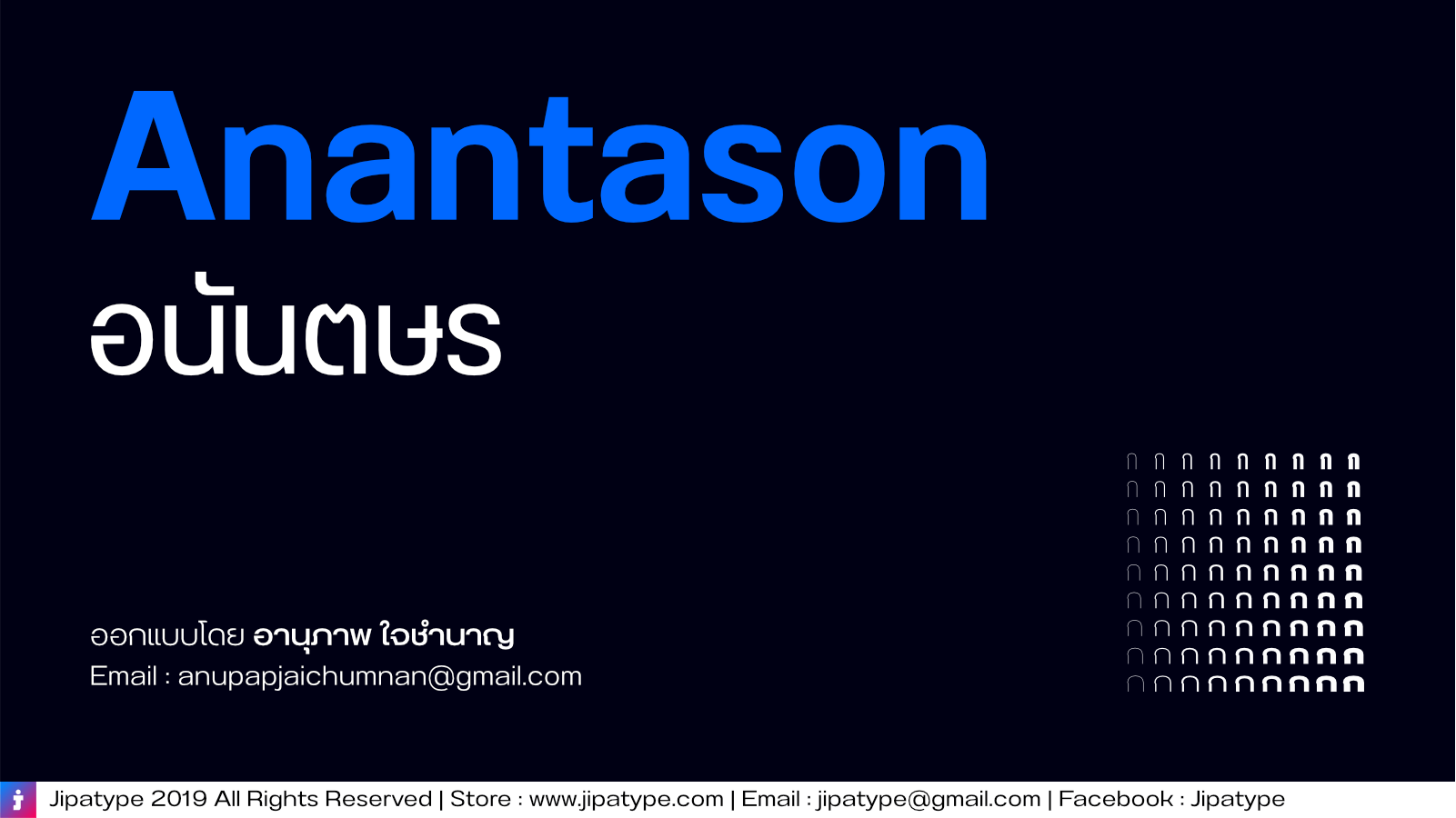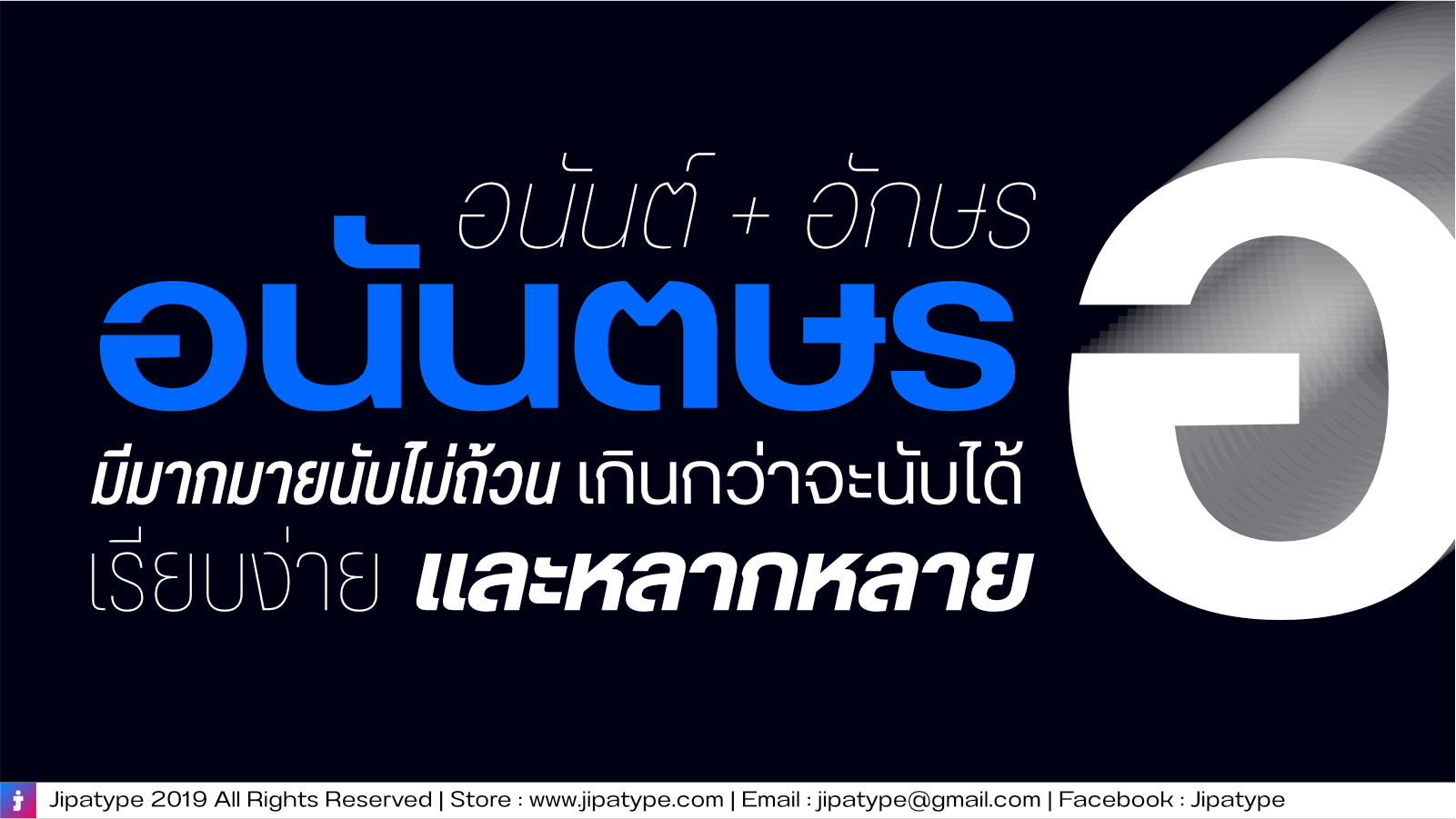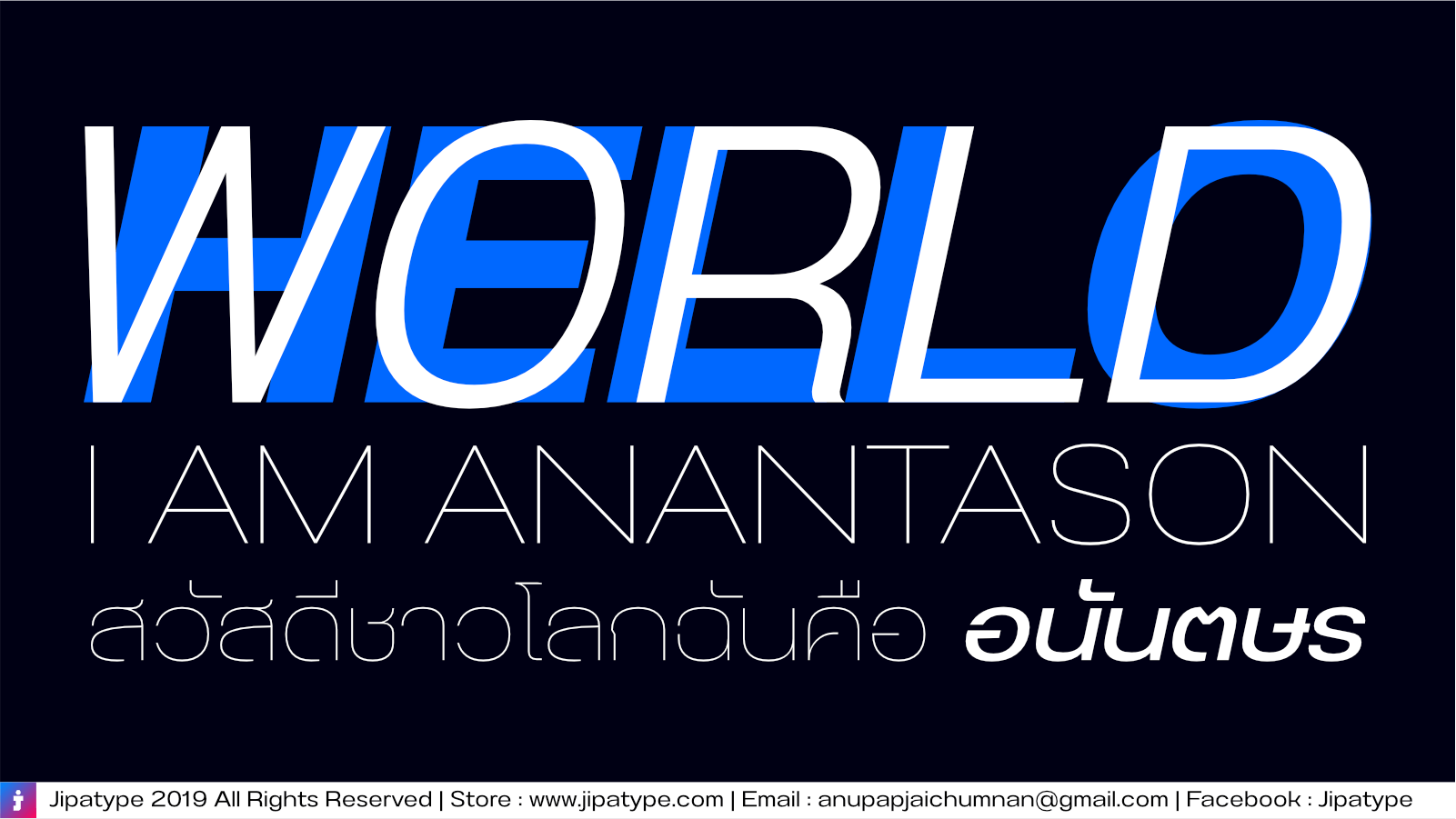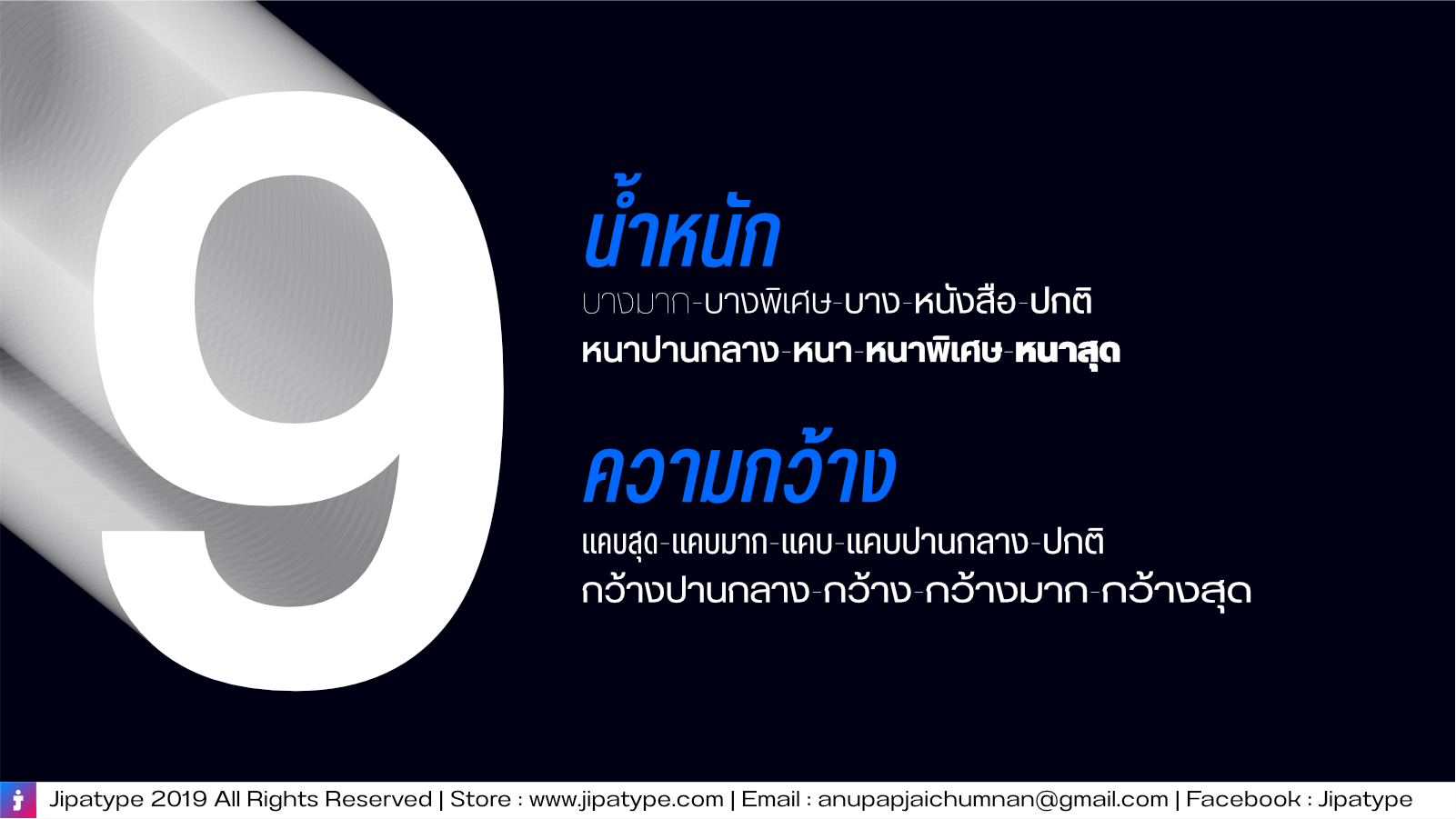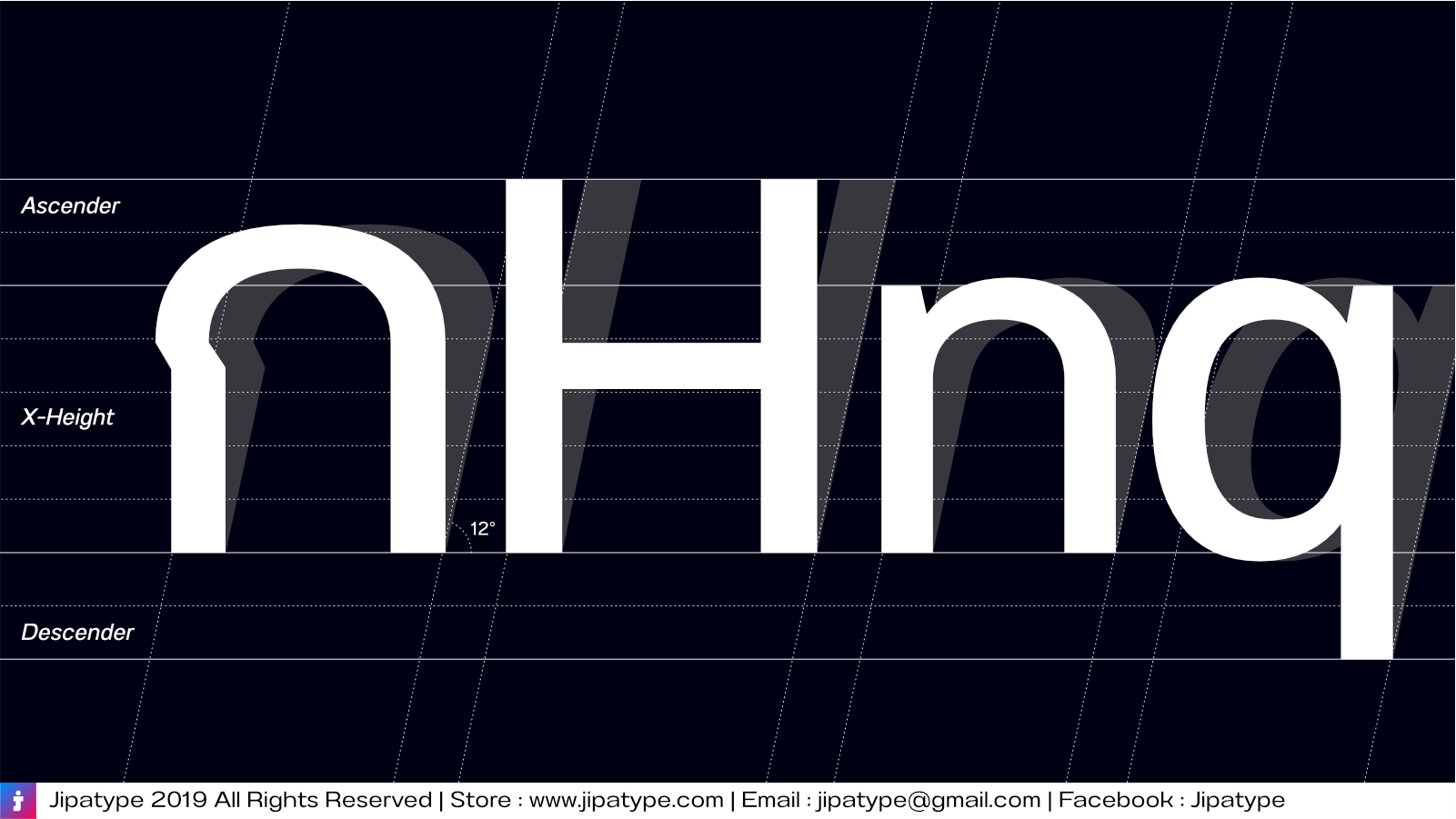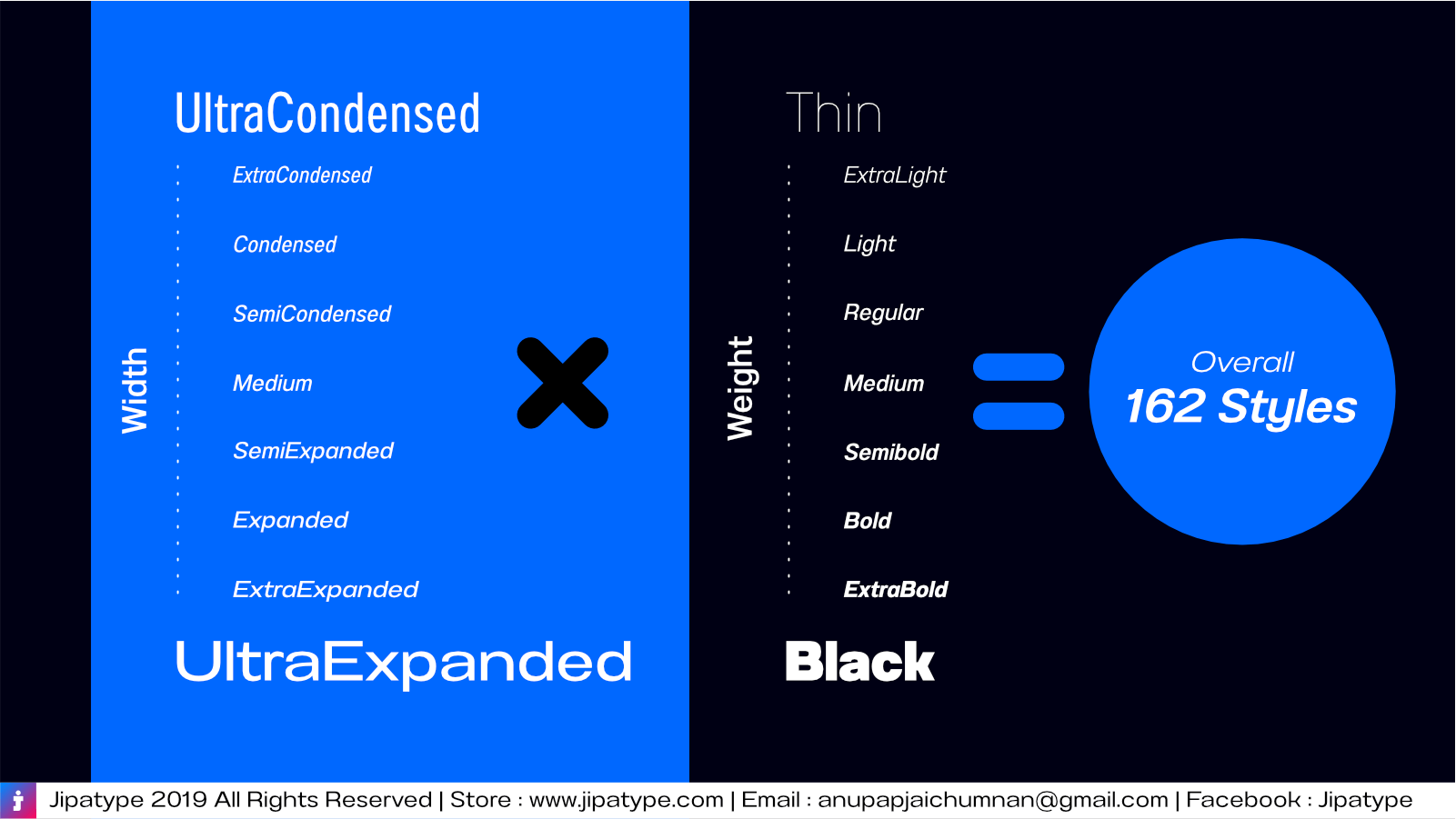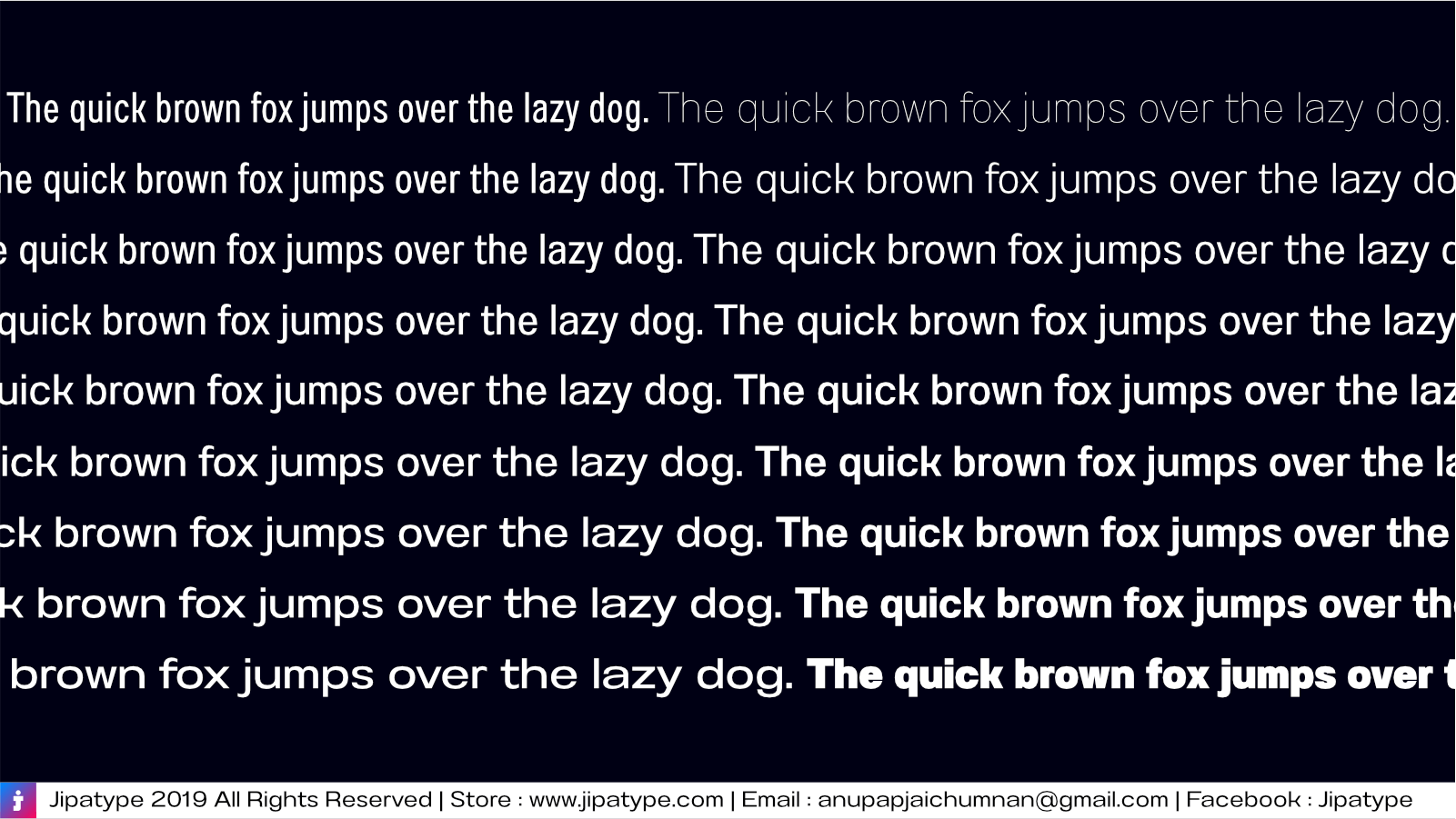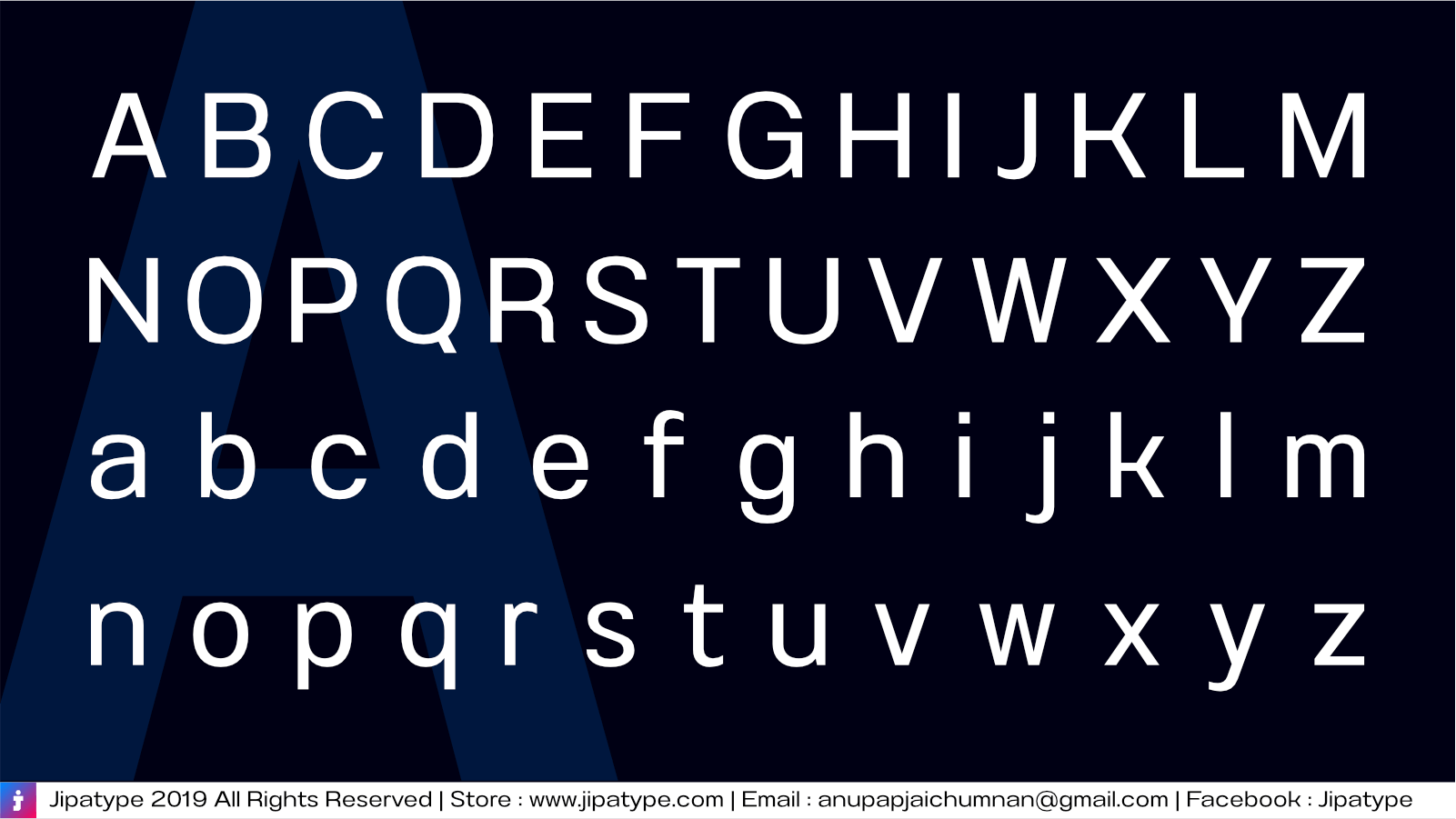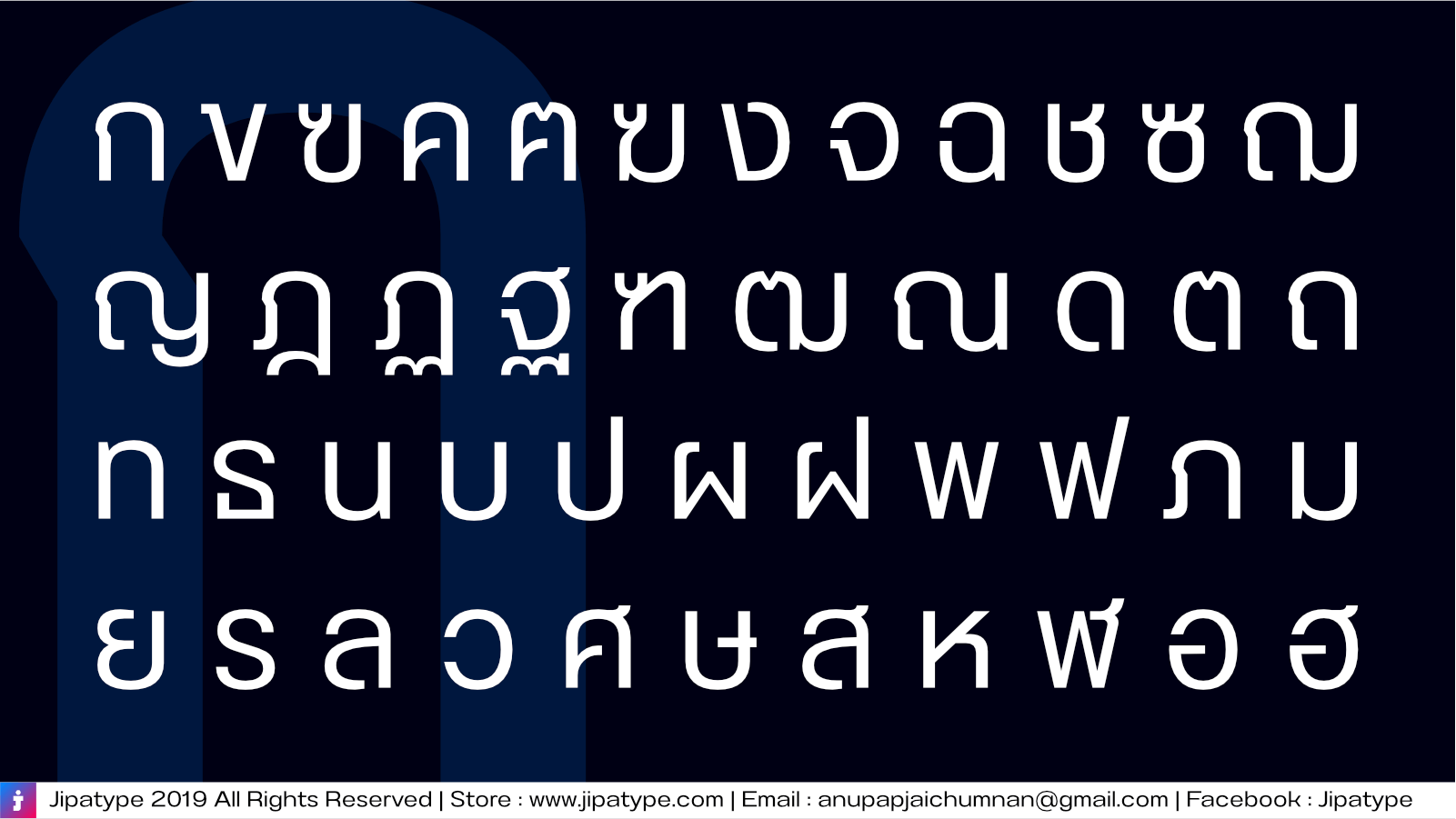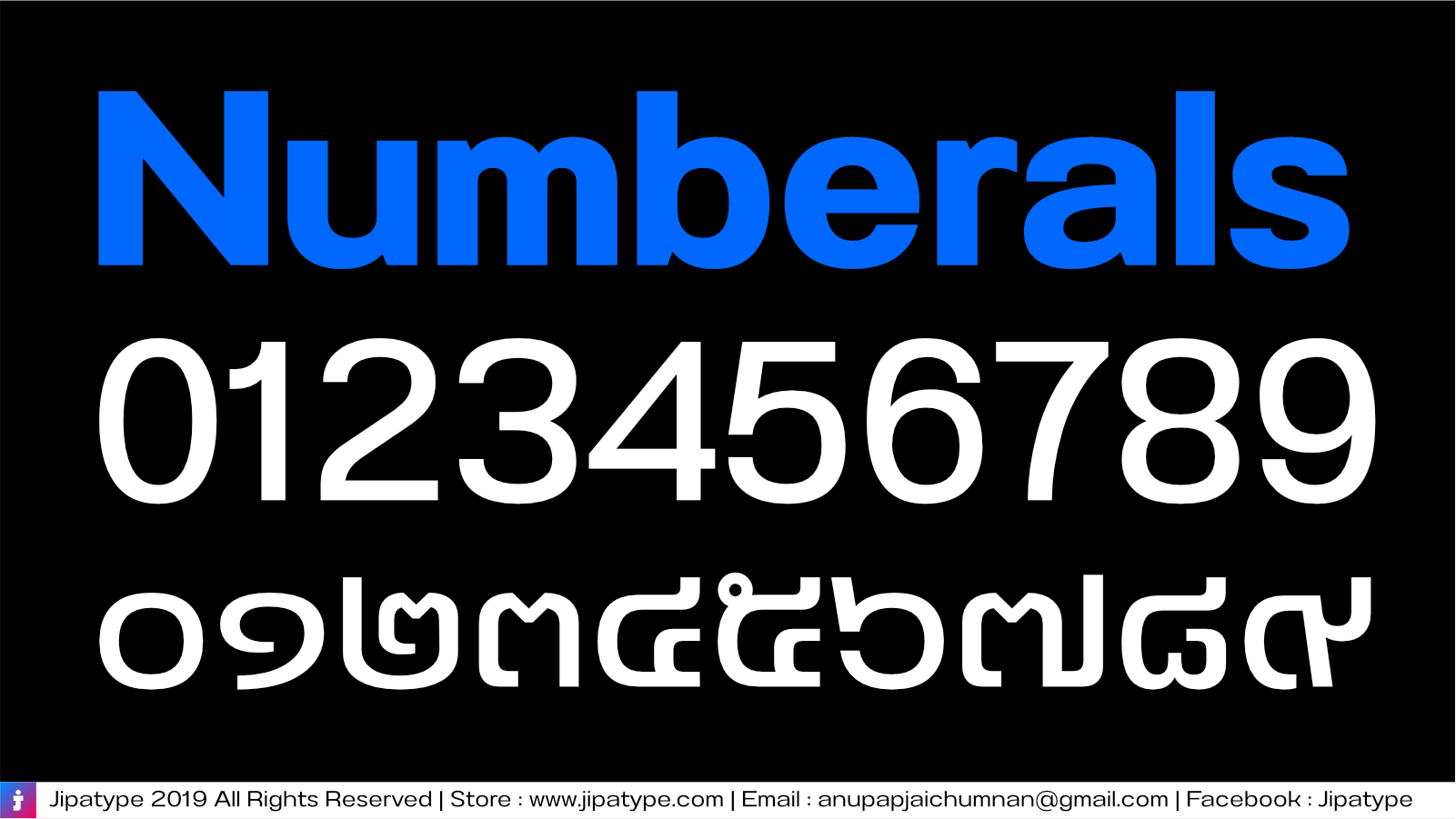
อนันตษร (Anantason Font)
Anantason มีสไตล์อันหลากหลายให้ได้เลือกใช้กันอย่างหนำใจ ดีไซน์เน้นความเรียบง่ายไม่ออกตัวแรง เพื่อส่งเสริมงานออกแบบของทุกๆ ท่านให้เด่นชัดขึ้น ในหลากหลายขนาดของชิ้นงาน ไม่ว่าท่านจะทำงานขนาดเล็กหรือใหญ่ กว้างหรือแคบ Anantason พร้อมตอบโจทย์ให้กับทุกๆ ท่านได้อย่างสมใจนึก
มีทั้งหมด 162 สไตล์
แบ่งออกเป็น ความกว้าง 9 ความกว้าง
น้ำหนัก 9 น้ำหนัก และตัวเอียงของแต่ละแบบ